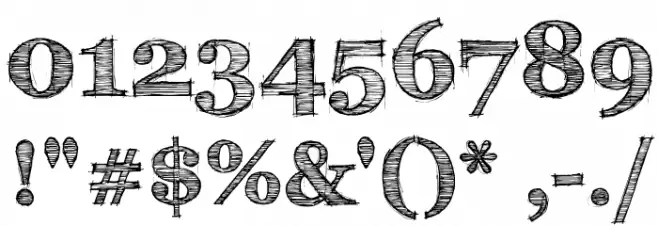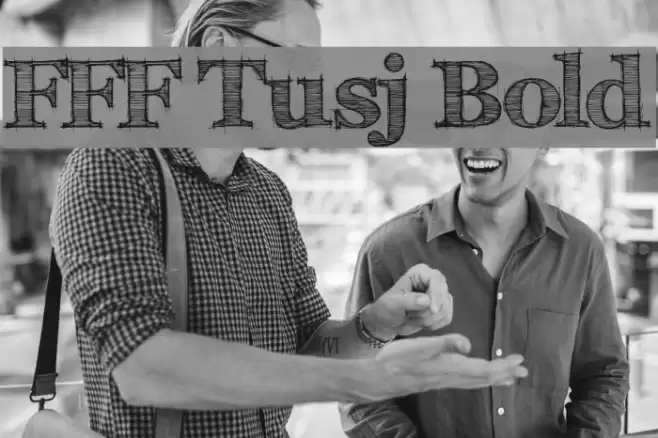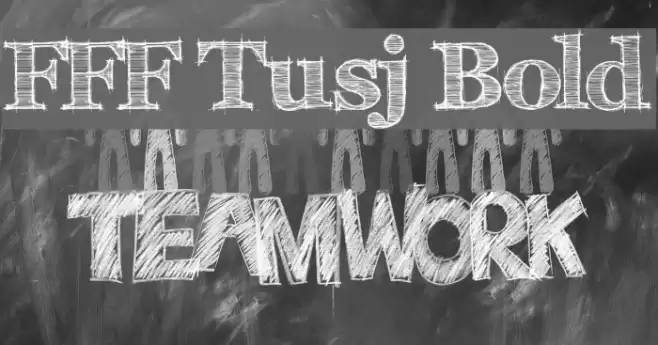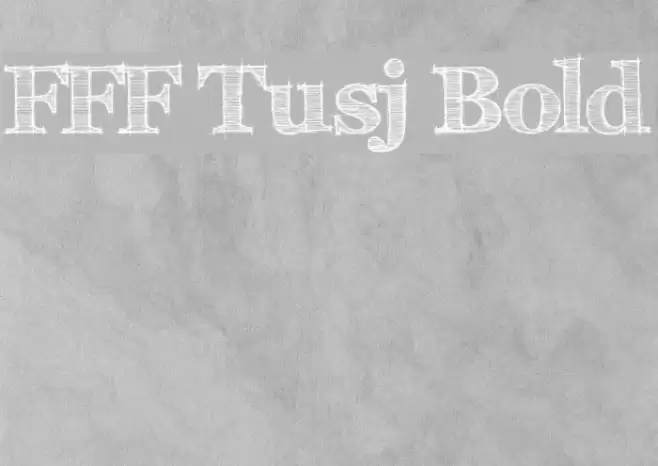
FFF Tusj Bold Font
✎ Handwritten
| श्रेणियाँ | Handwritten |
| समग्र शैली | Decorative |
| उपयोग का मामला | Headlines, Logos |
| सुझाए गए प्रोजेक्ट | Ideal for creative projects such as posters, invitations, and artistic branding that require a unique, handcrafted look. |